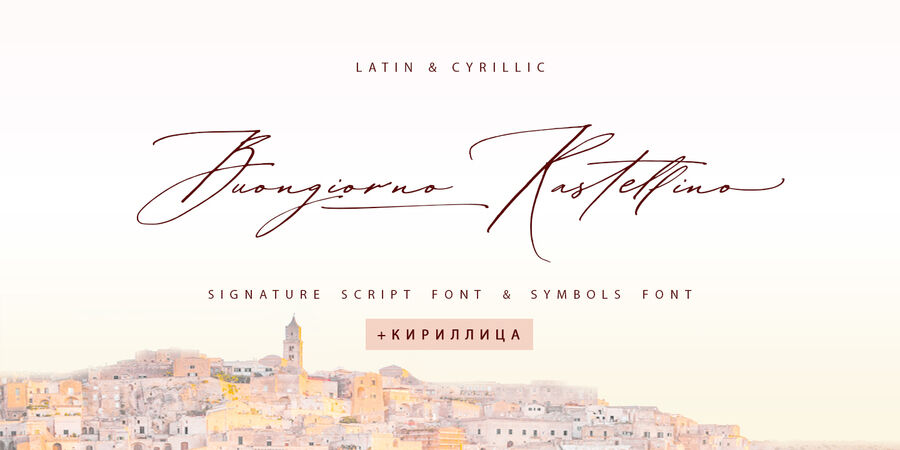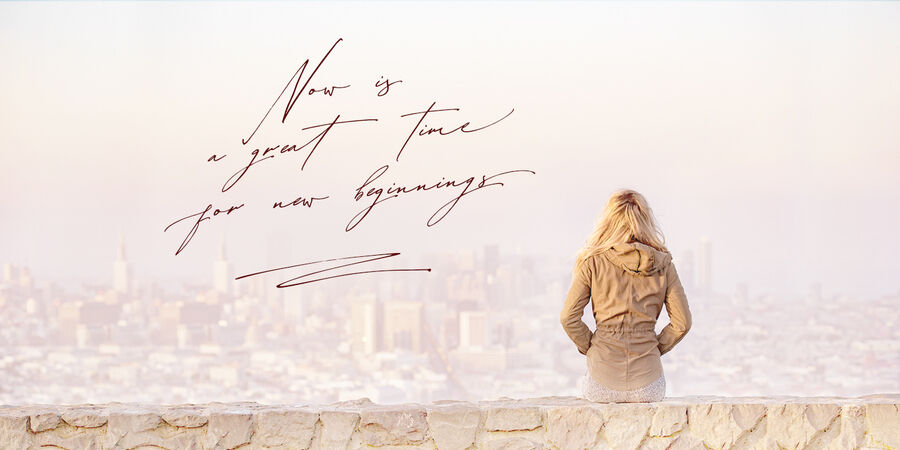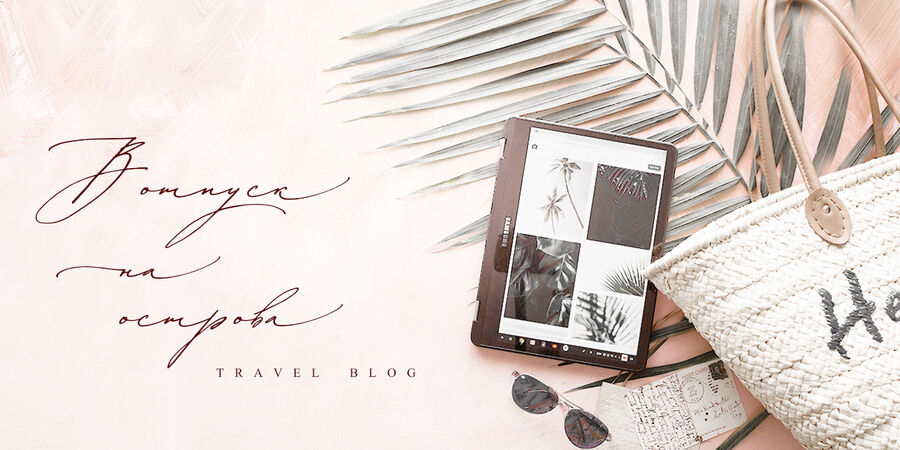
Скорописний курсив Buongiorno Rastellino з кирилицею стане ідеальним рішенням для вашого елегантного, жіночного та витонченого дизайну. Шрифтовая пара Buongiorno Rastellino font Cyrillic + Buongiorno Rastellino Symbols ідеально підійде для вашого весільного запрошення, монограм, брендингу, логотипів, візиток, соціальних мереж і упаковки. Buongiorno Rastellino Cyrillic включає повний набір великих літер, 3 набори малих літер з яких 2 сети малих літер з початковими і кінцевими завитками, цифр, великий діапазон розділових знаків і 40 лігатур, які надають реалістичний стиль написання. Для створення необхідної форми просто введіть букву з цифрою, наприклад, а1, б1 в1 ... Після цього виберіть слово і застосуєте Open Type Features в таких програмах, як Adobe Illustrator, Photoshop, та інші) Також кирилична частина шрифту містить 31 рукописну лігатуру. Buongiorno Rastellino Symbols – це шрифт, який містить 36 намальованих від руки елементів, ілюстрацій і штрихів, які допоможуть зробити ваш дизайн більш оригінальним. Багатомовна підтримка 31 мови, включно з кирилицею для російської, української, білоруської та болгарської мов. Шрифт розробила Ірина Двілюк у 2020 році.
Асоціації з сімейством шрифтів Buongiorno RastellinoОсобистість і характер гарнітури:
неформальний, радісний, свіжий, тонкий, повітряний, летячий, швидкий, динамічний, натхненний, ліричний, чуттєвий, емоційний, музичний, поетичний, артистичний, пристрасний, творчий, лихий, розв'язний, сміливий, оригінальний, вільний, самобутній, різкий, колоритний, живий, темпераментний, активний, стрімкий, прозорий, швидкісний, моторний, біжить, розмашистий, весняний, неохайний, характерний, вернакулярний, святковий, весільний, романтичний, ритмічний, легкий, жіночий, грайливий, мажорний, легковажний, вітряний, інтимний, сентиментальний, танцюючий, цікавий, красивий, елегантний, жіночний, епістолярний, крихкий, крафтовий, сексуальний, художній, гарненький, симпатичний, артізанальний, рослинний, худий, дівчачий
свято, лірика, сувенір, швидкість, поезія, література, мистецтво, квіти, танець, дієта, музика, косметика, кафе, кохання, вірші, вино, балет, весна, романтика, сукня, краса, Інстаграм, мода, реклама, розваги, виставка, одяг, перукарня, хенд мейд, сад, щоденник, принцеса, театр, подарунки, відпочинок, весілля, АСМР, графіка, ілюстрація, ранок, світанок, пейзаж Гарнітура має ознаки стилів: